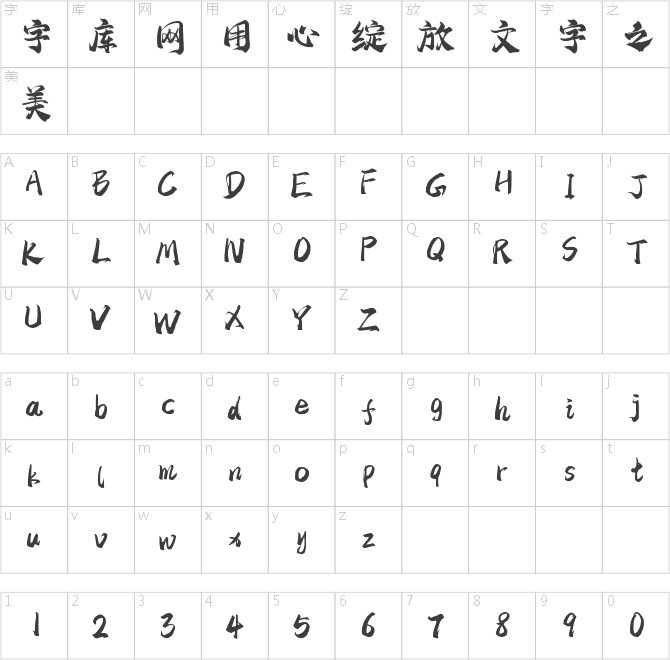
字魂240號(hào)-清夢(mèng)手書是一款手寫字。字體筆觸飽滿有力,筆勢(shì)連綿,筆畫粗細(xì)過(guò)渡自然,氣勢(shì)浩然縹緲,適用于文化類的宣傳設(shè)計(jì)、商業(yè)類品牌的廣告和產(chǎn)品包裝設(shè)計(jì)。
字魂240號(hào)-清夢(mèng)手書字體zihun240hao-qingmengshoushu字庫(kù)是一款讓人賞心悅目、百看不厭的中文字體,適合各類廣告和產(chǎn)品包裝設(shè)計(jì)應(yīng)用,字體大小24.95MB,格式為ttf字體,上傳用戶是徐明澤,作者/版權(quán)方為字魂